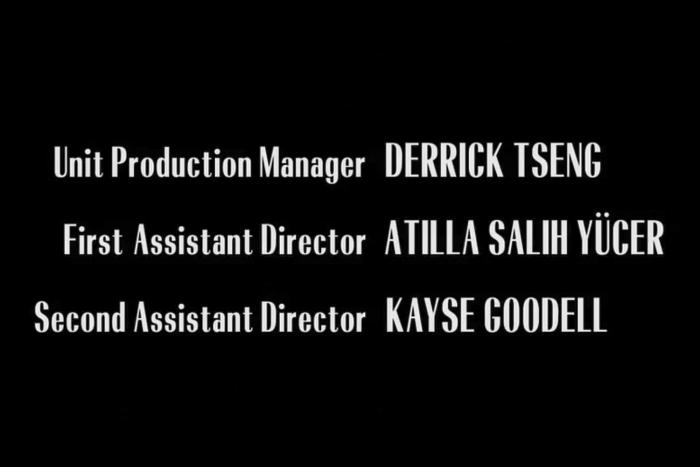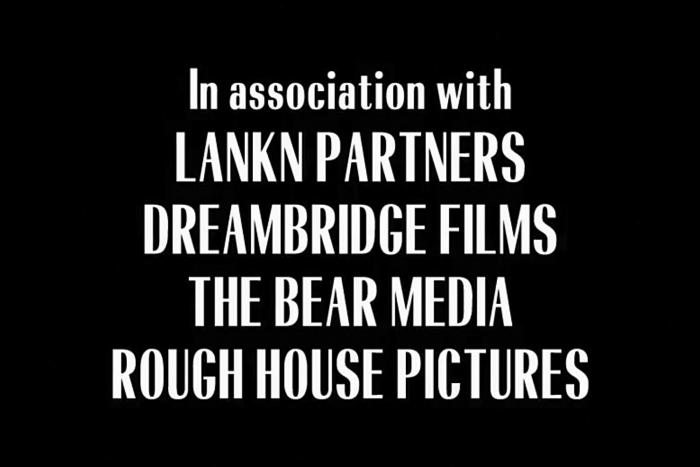
Serifenlose aus Filmabspann
Ich denke mal den Abspann hat jemand in Photoshop gesetzt der nicht ganz soviel mit Typografie am Hut hatte wie wir … die Schrift finde ich aber ganz spannend.
Auf jeden Fall auch interessant - wobei mir hier etwas der Kontrast der Radiant fehlt.